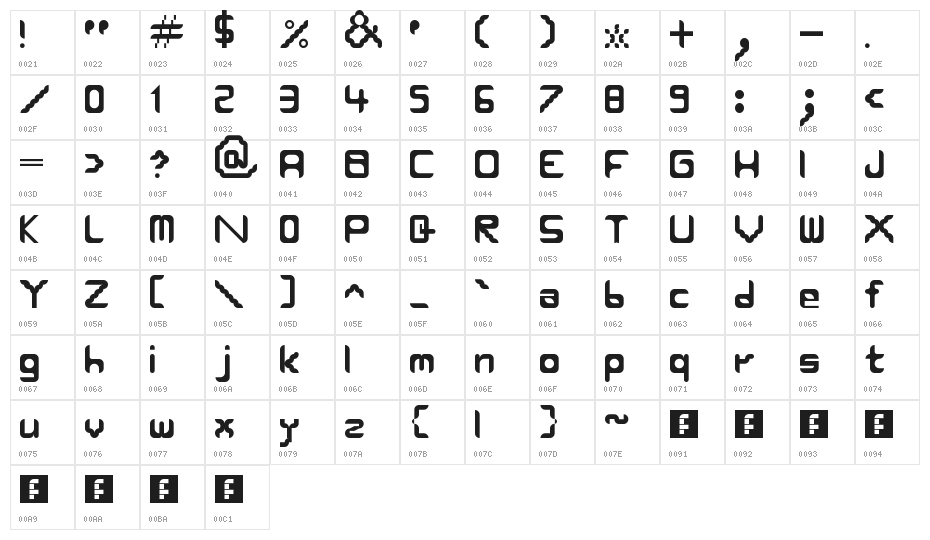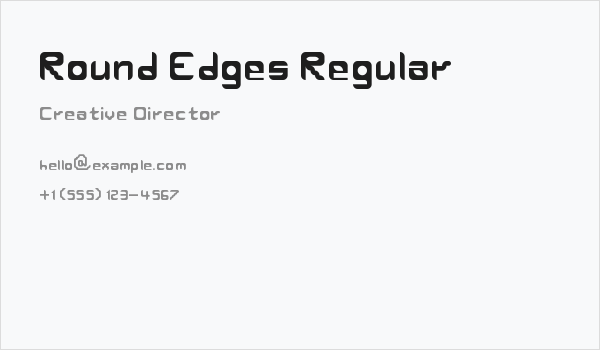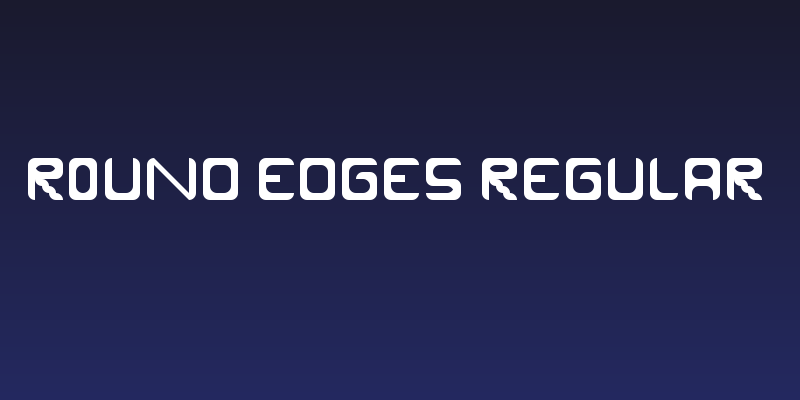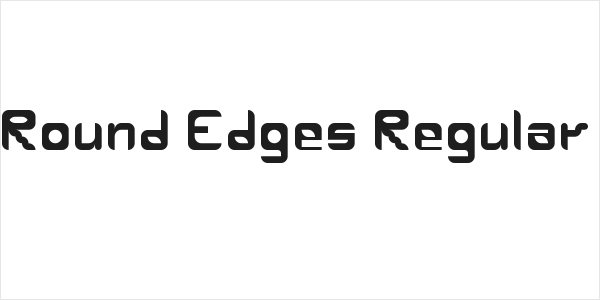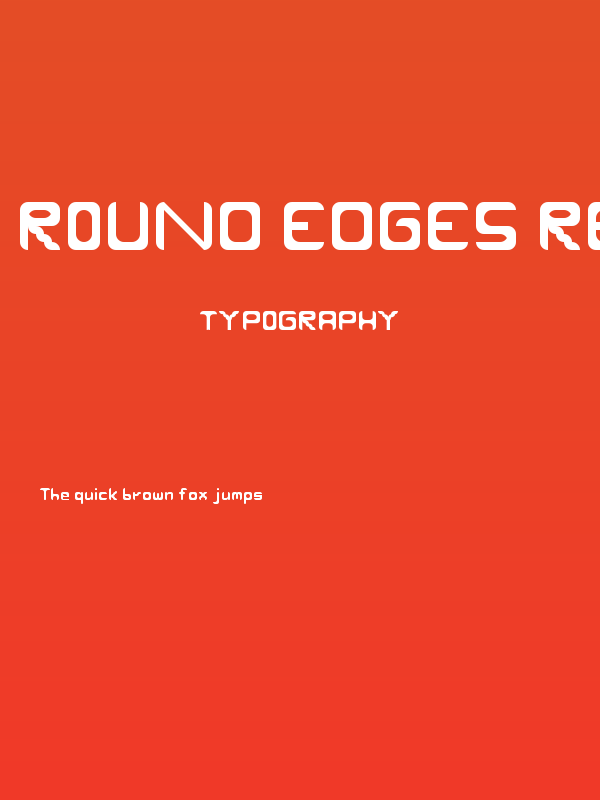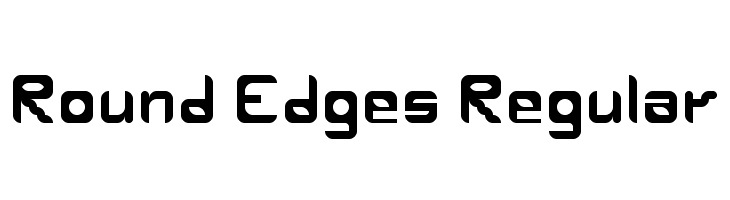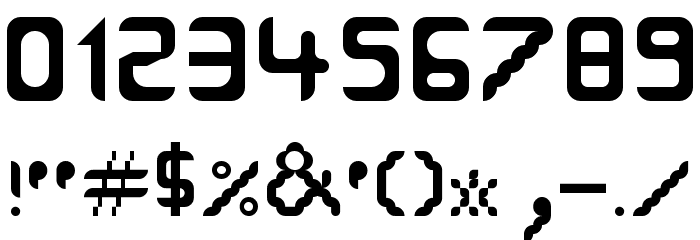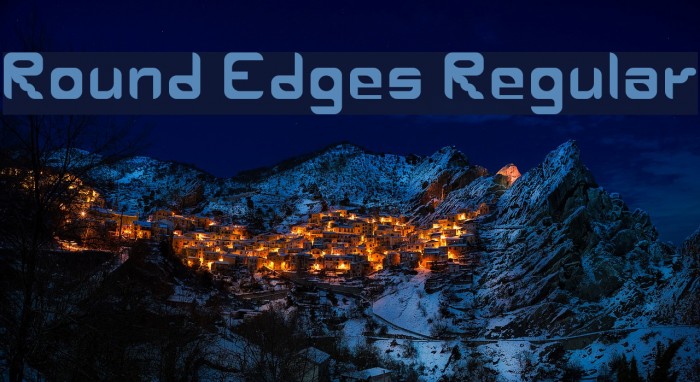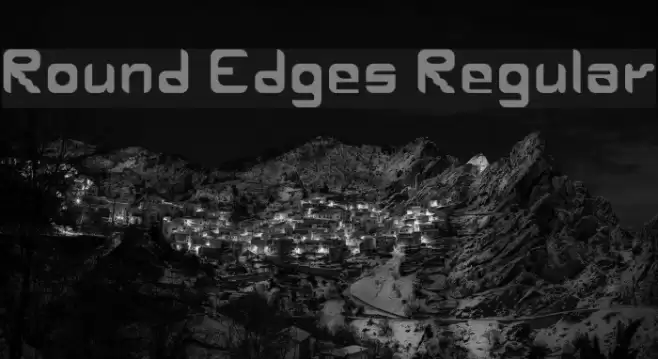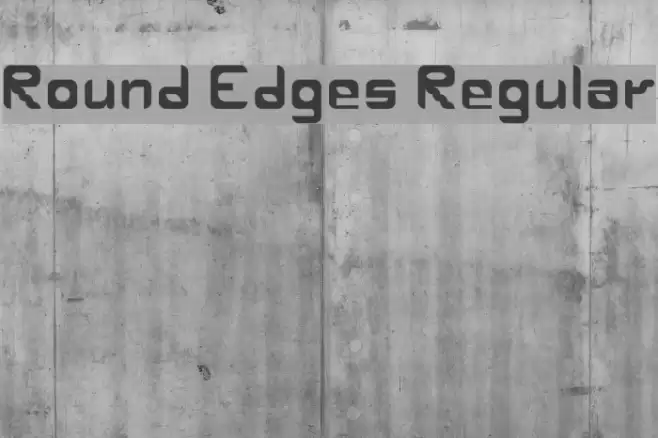
Round Edges Regular Font
| Cas d'utilisation | Headlines, Logos, Branding |
| Projets proposés | Ideal for branding, logos, headlines, and digital media where a modern and approachable look is desired. |